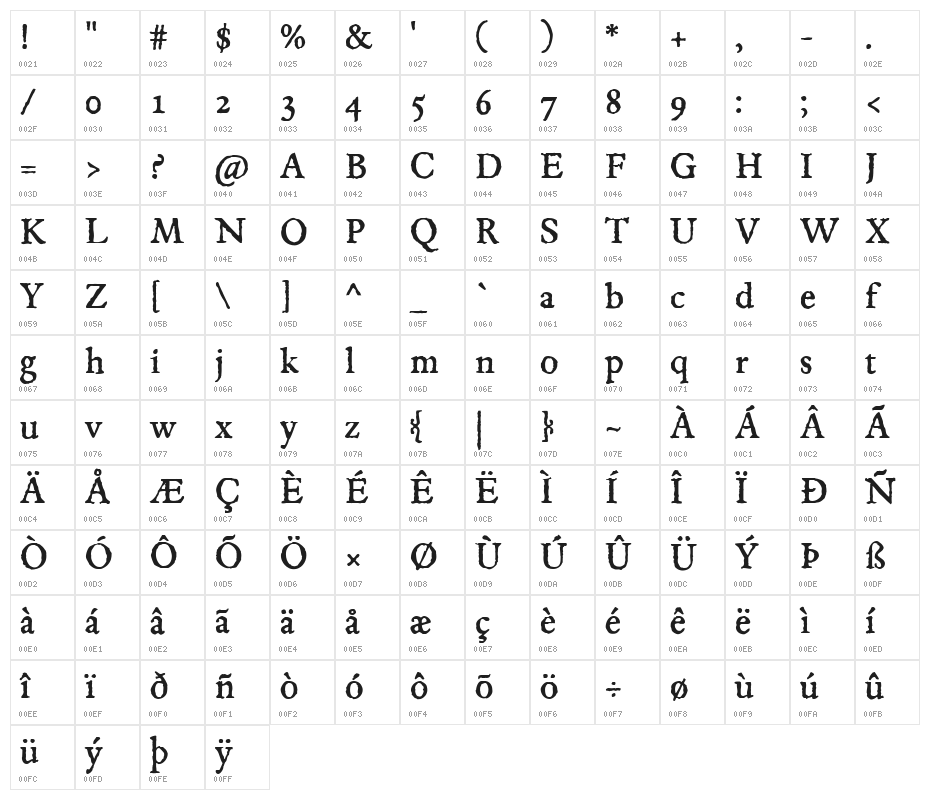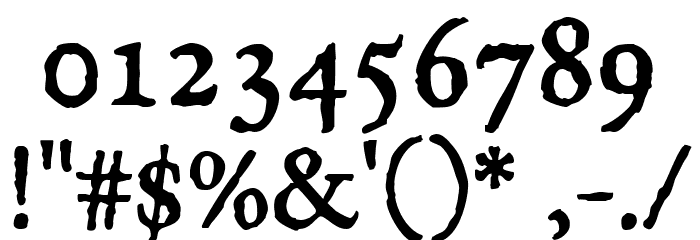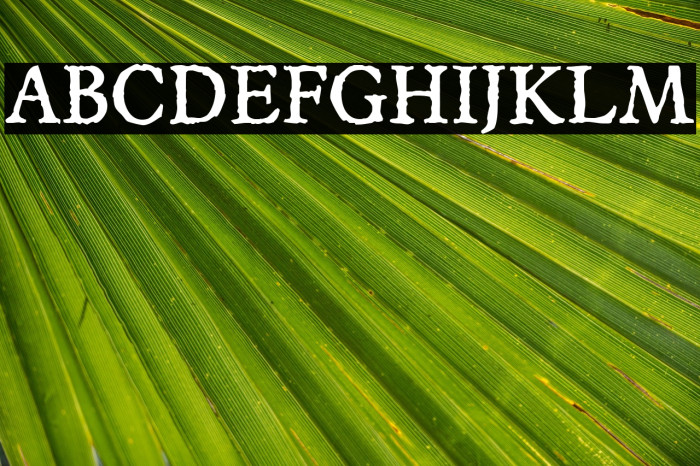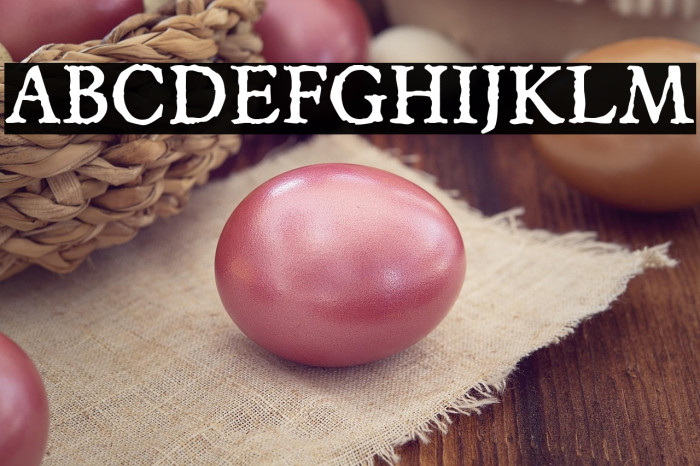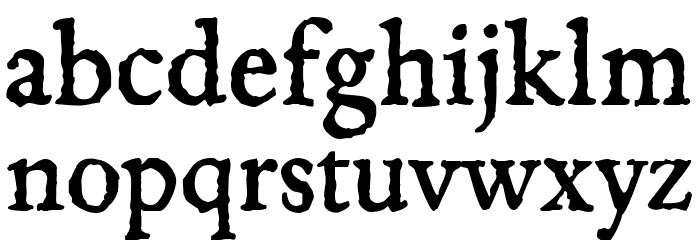
JMHEspinosa-Regular Font
| Projets proposés | Ideal for projects that require a rustic or historical touch, such as posters, book covers, branding for artisanal products, or any design needing a handcrafted feel. |